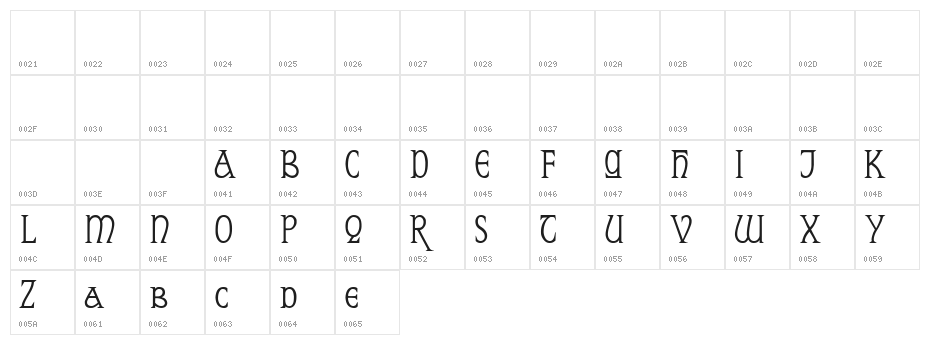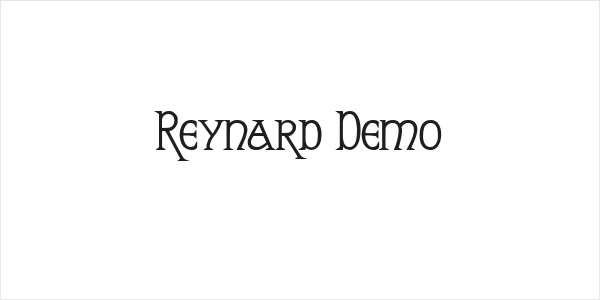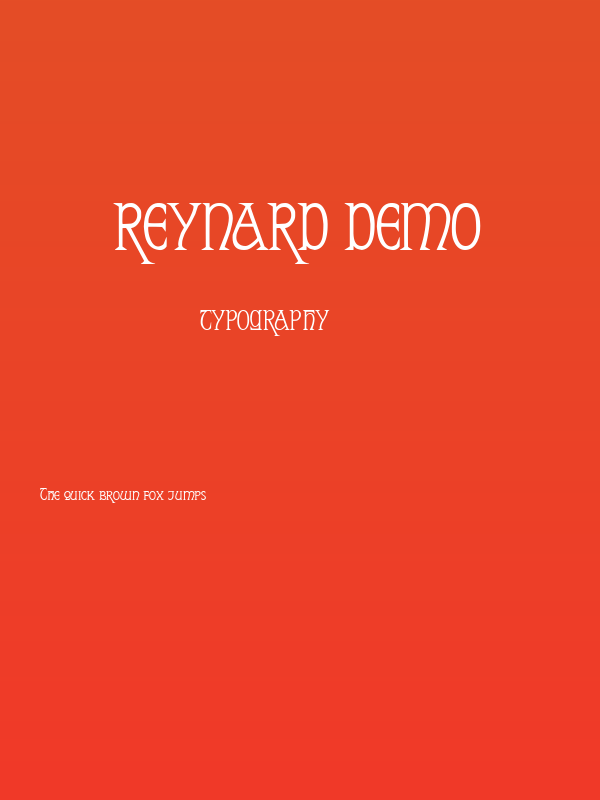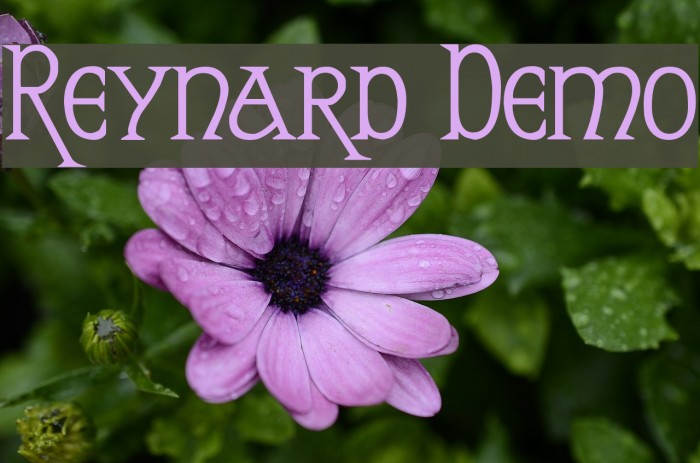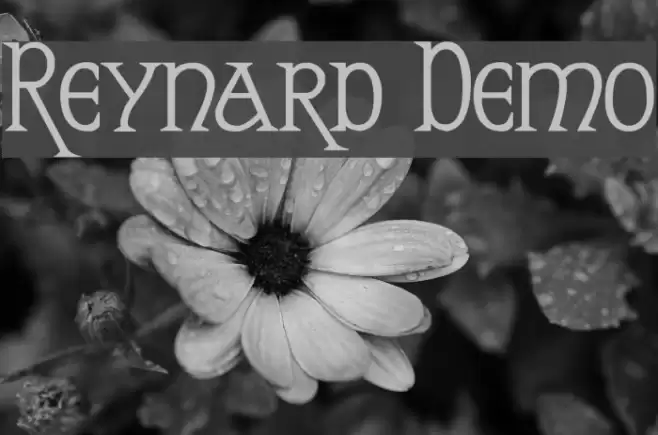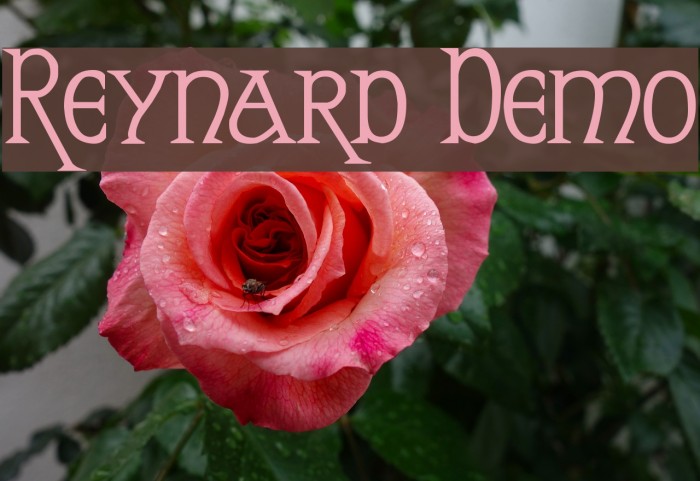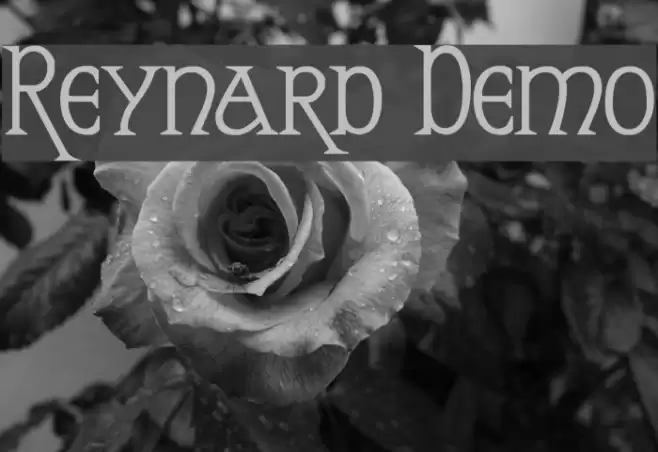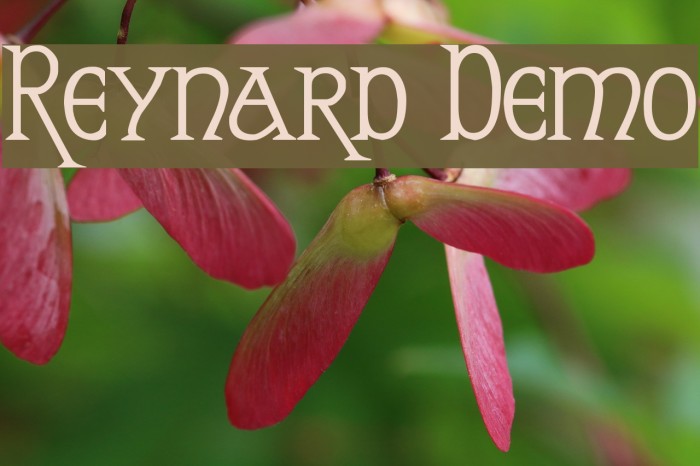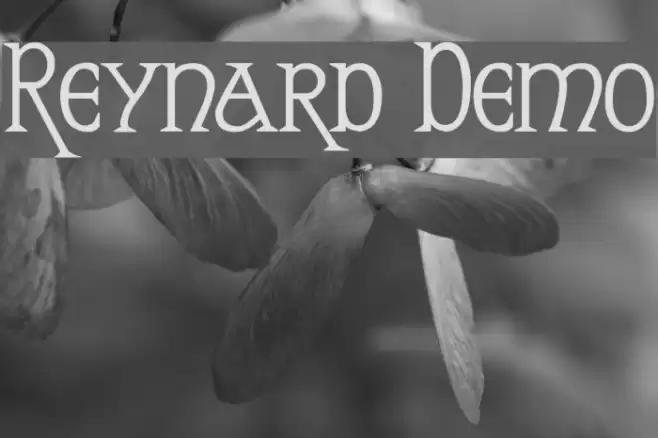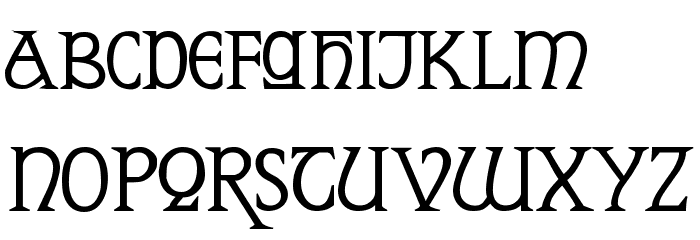
Reynard Demo Font
| Caso de uso | Headlines, Logos, Editorial design |
| Projetos propostos | Ideal for branding, editorial design, and creative projects that require a sophisticated and unique typeface. |